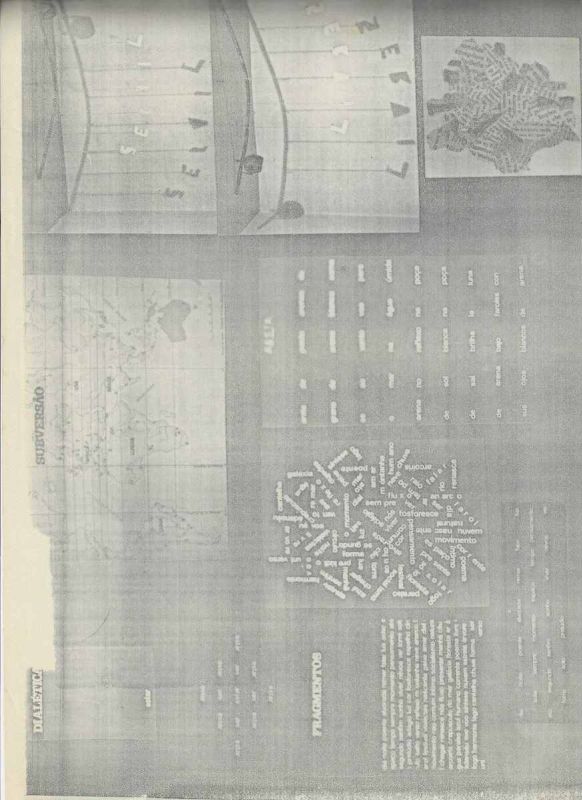
Subversão é uma impressão experimental de Herculano Vilas Boas que reúne poesia visual, cartografia, tipografia, colagem gráfica e organização espacial da linguagem em uma composição de forte conteúdo político e conceitual.
Subversão é uma impressão experimental de Herculano Vilas Boas que reúne poesia visual, cartografia, tipografia, colagem gráfica e organização espacial da linguagem em uma composição de forte conteúdo político e conceitual. A obra articula palavras, mapas, diagramas e estruturas textuais que sugerem deslocamentos de sentido, questionamentos sobre poder, território, informação e formas de organização social. A fragmentação dos elementos visuais e verbais cria um campo de leitura não linear, característico das pesquisas ligadas à poesia experimental brasileira e às propostas de expansão dos meios de comunicação artística desenvolvidas no final da década de 1970. O título Subversão atua como chave interpretativa para uma obra que desafia sistemas estabelecidos de leitura e percepção. Por meio da sobreposição de referências geográficas, linguísticas e ideológicas, Herculano Vilas Boas constrói uma cartografia crítica do pensamento contemporâneo, transformando a página em espaço de investigação estética, política e poética. A obra integra a produção experimental do artista voltada à renovação da linguagem visual e à democratização dos processos criativos.EnglishSubversão is an experimental print by Herculano Vilas Boas that brings together visual poetry, cartography, typography, graphic collage and spatial organization of language in a composition with strong political and conceptual content. The work combines words, maps, diagrams and textual structures that suggest shifts in meaning and reflections on power, territory, information and forms of social organization. The fragmentation of visual and verbal elements creates a non linear reading field, characteristic of Brazilian experimental poetry and of artistic communication practices developed in the late 1970s. The title Subversão functions as an interpretative key for a work that challenges established systems of reading and perception. Through the overlapping of geographic, linguistic and ideological references, Herculano Vilas Boas creates a critical cartography of contemporary thought, transforming the page into a space for aesthetic, political and poetic investigation. The work belongs to the artist
s experimental production dedicated to renewing visual language and expanding creative communication processes.Texto de ObservaçãoPortuguêsImpressão experimental composta por elementos cartográficos, textos, palavras e diagramas organizados segundo princípios da poesia visual. A obra aborda questões de comunicação, território, crítica social e transformação cultural por meio de uma estrutura gráfica aberta e multidirecional.EnglishExperimental print composed of cartographic elements, texts, words and diagrams organized according to visual poetry principles. The work addresses communication, territory, social criticism and cultural transformation through an open and multidirectional graphic structure.
Impressão experimental composta por elementos cartográficos, textos, palavras e diagramas organizados segundo princípios da poesia visual. A obra aborda questões de comunicação, território, crítica social e transformação cultural por meio de uma estrutura gráfica aberta e multidirecional.EnglishExperimental print composed of cartographic elements, texts, words and diagrams organized according to visual poetry principles. The work addresses communication, territory, social criticism and cultural transformation through an open and multidirectional graphic structure.
Subversão is an experimental print by Herculano Vilas Boas that brings together visual poetry, cartography, typography, graphic collage and spatial organization of language in a composition with strong political and conceptual content.